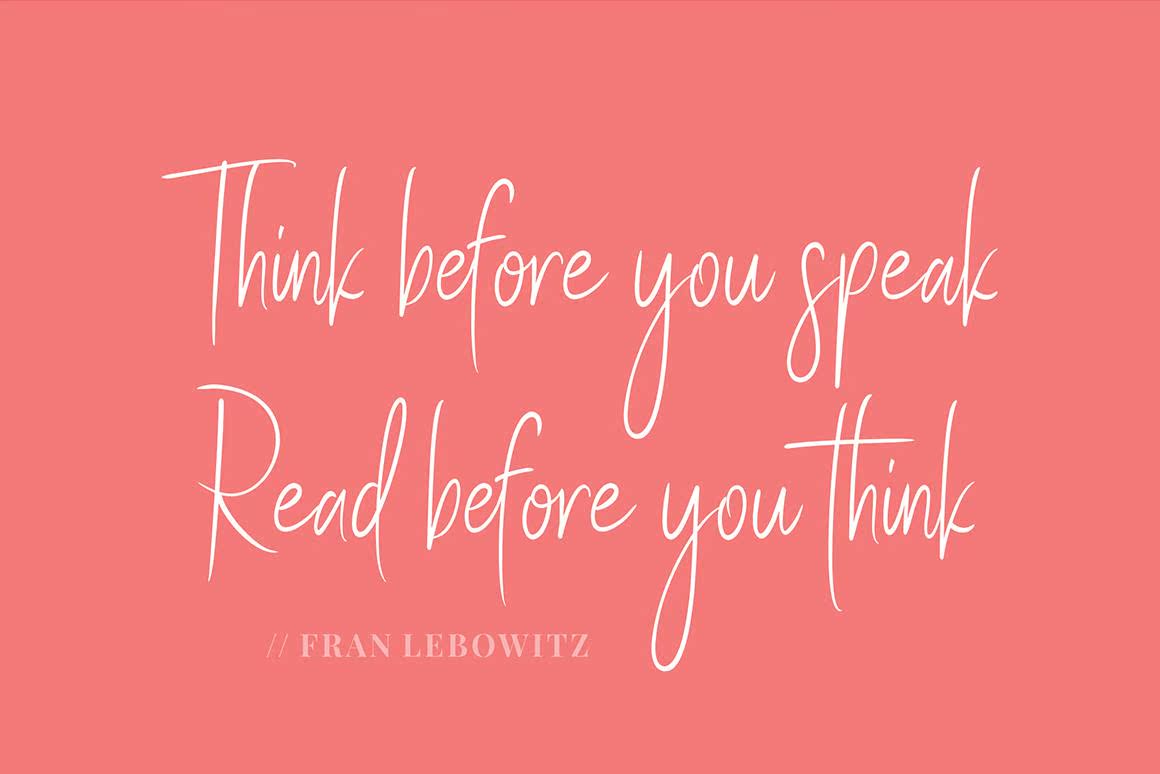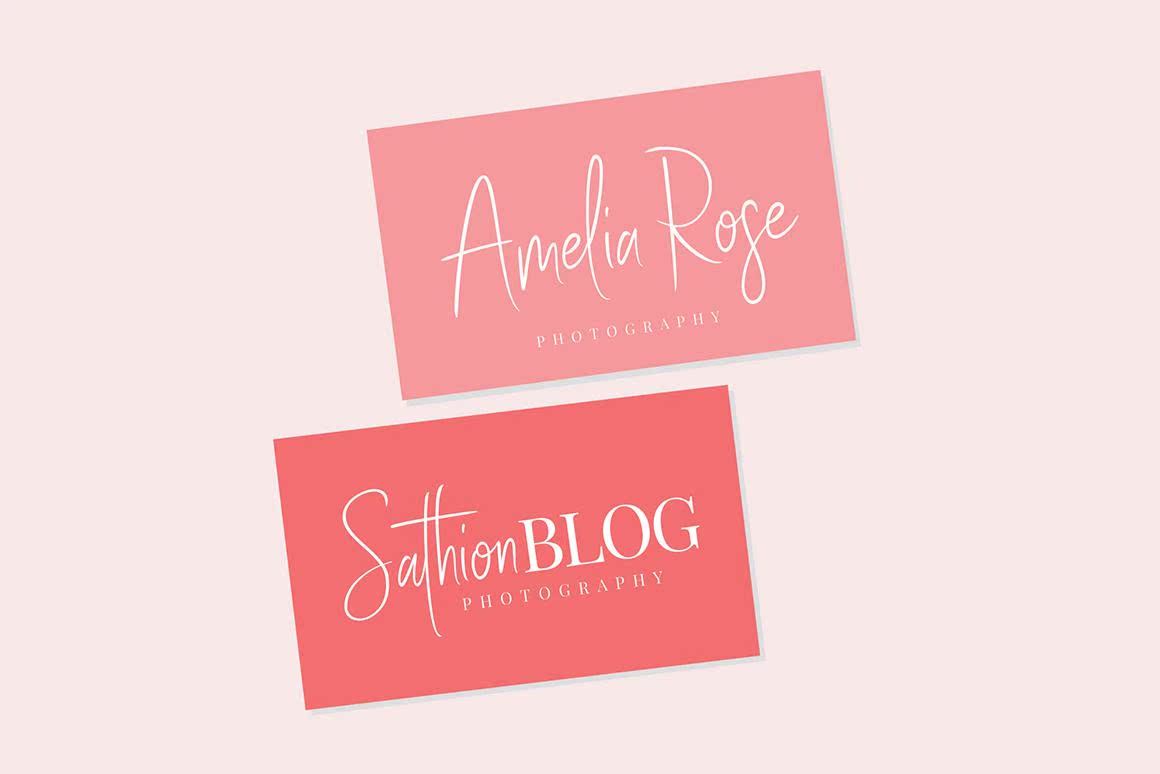
Stayclass是一个巨大而简单的手写体脚本字体;当代时尚的Stayclass可用于多种项目类型。此优雅的字体在标题或文本中注册并具有良好的可读性。此字体将完善博客、社交媒体、品牌、婚礼邀请、卡片集等不同的项目。Stayclass字体大而简单,可写性强;当代时尚的Stayclassylook适用于多种项目类型。此优雅的字体是可注册的,并且在头条新闻或博客文本中非常流行。此字体将完善博客、社交媒体、品牌、婚礼邀请、名片等不同的项目。